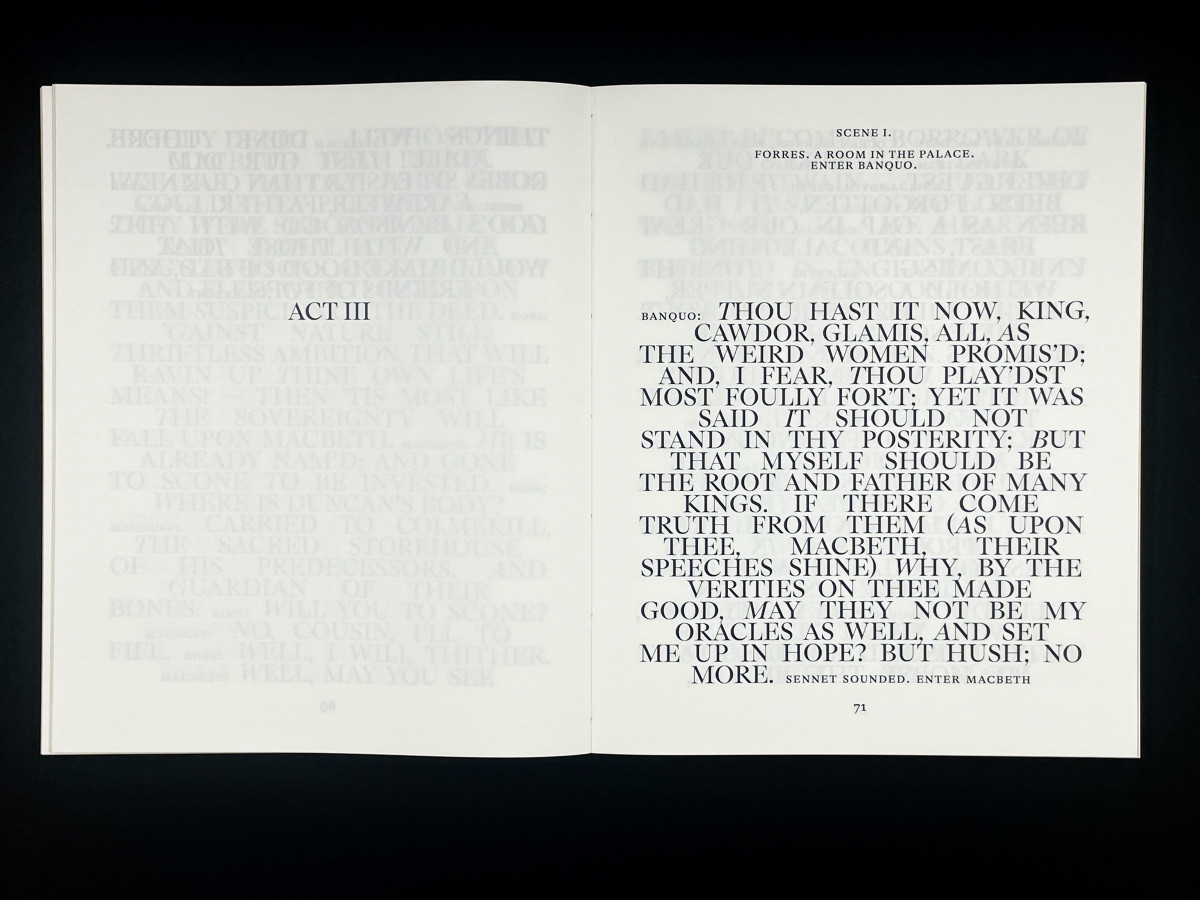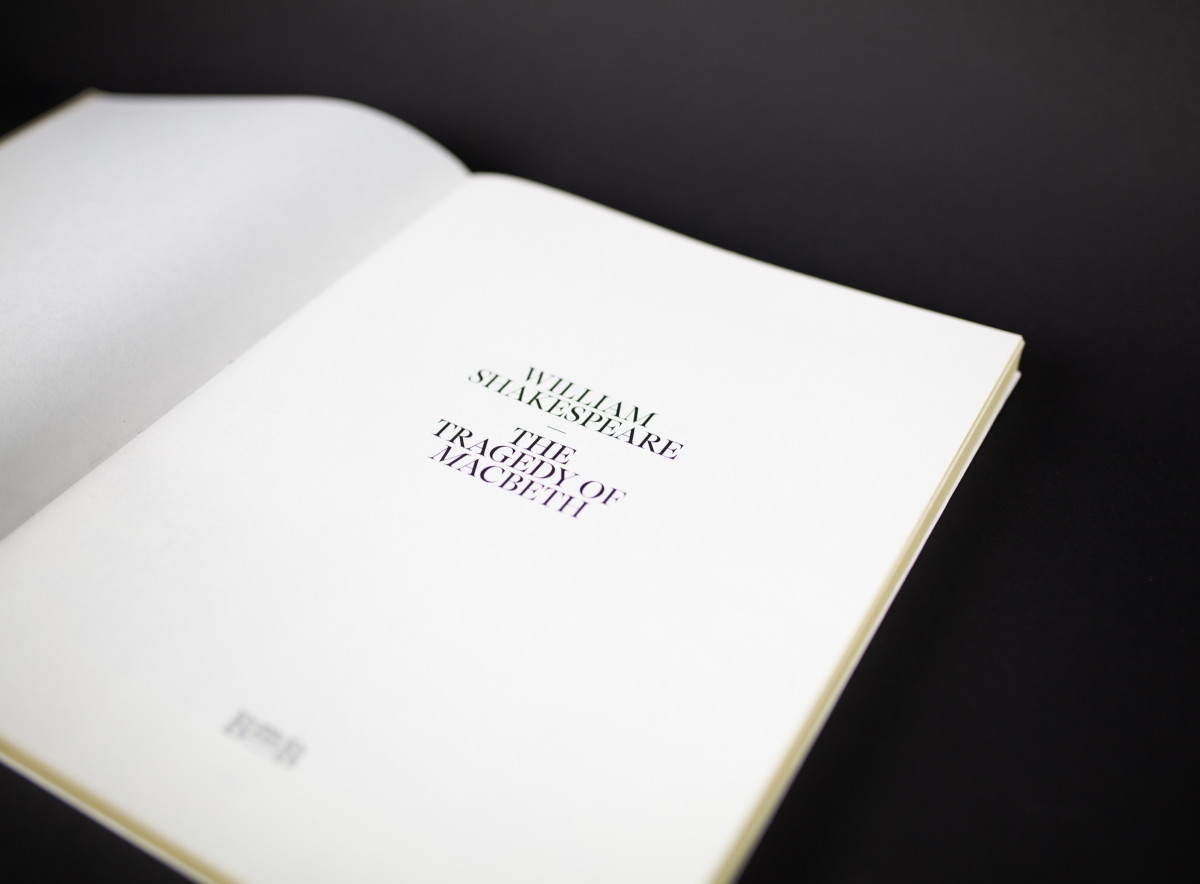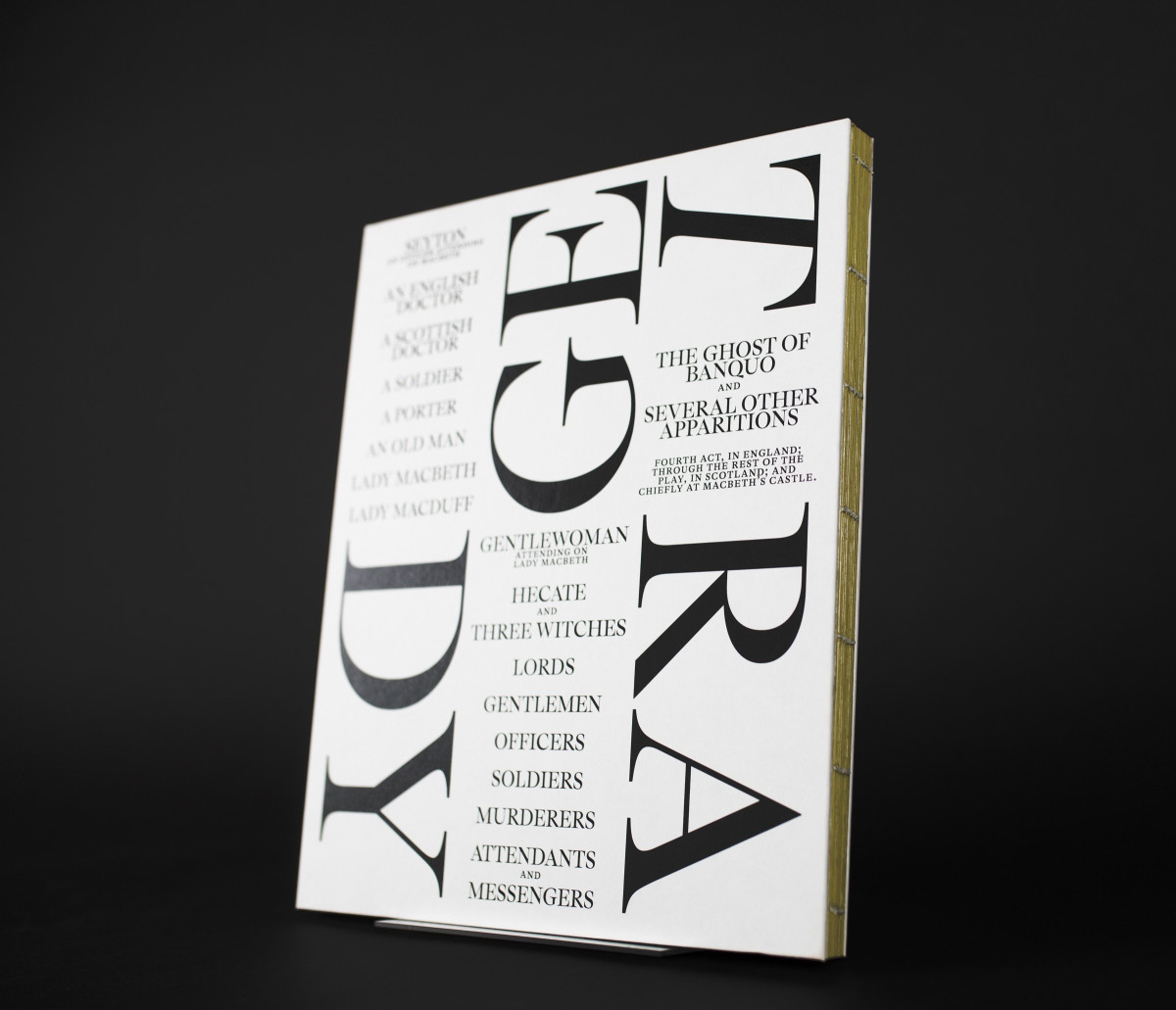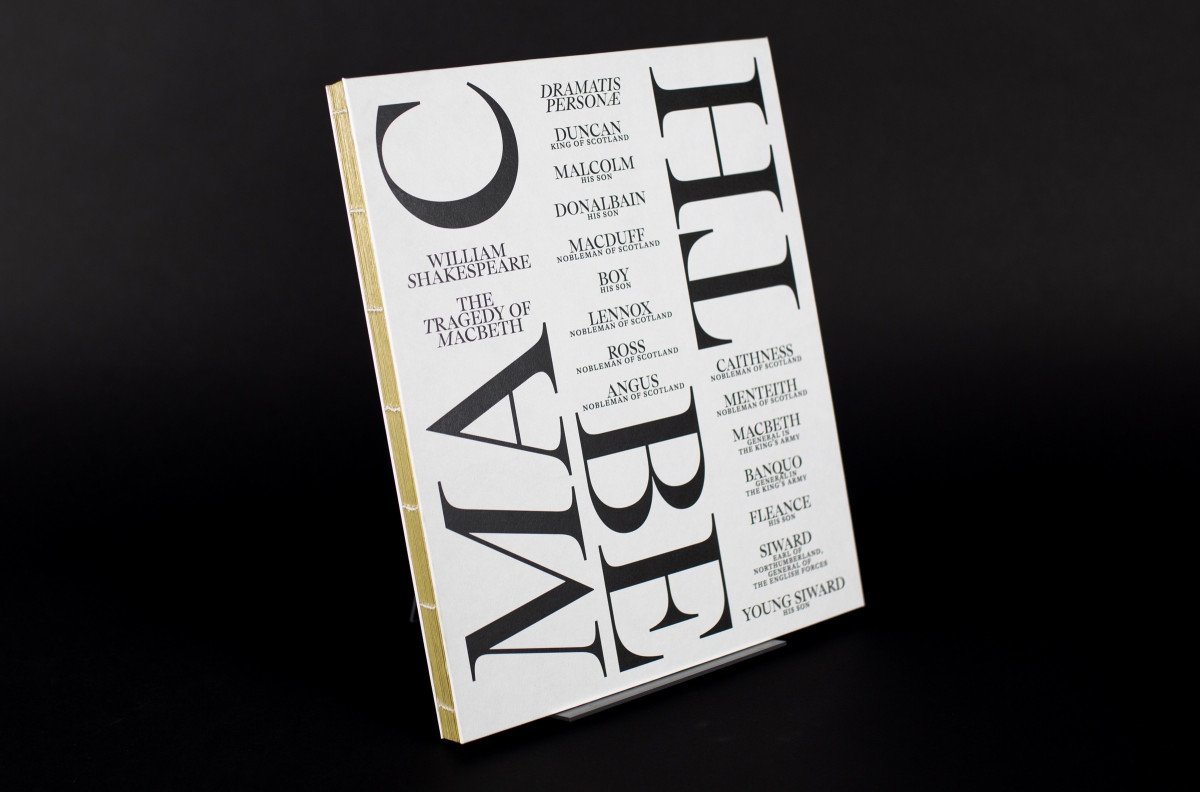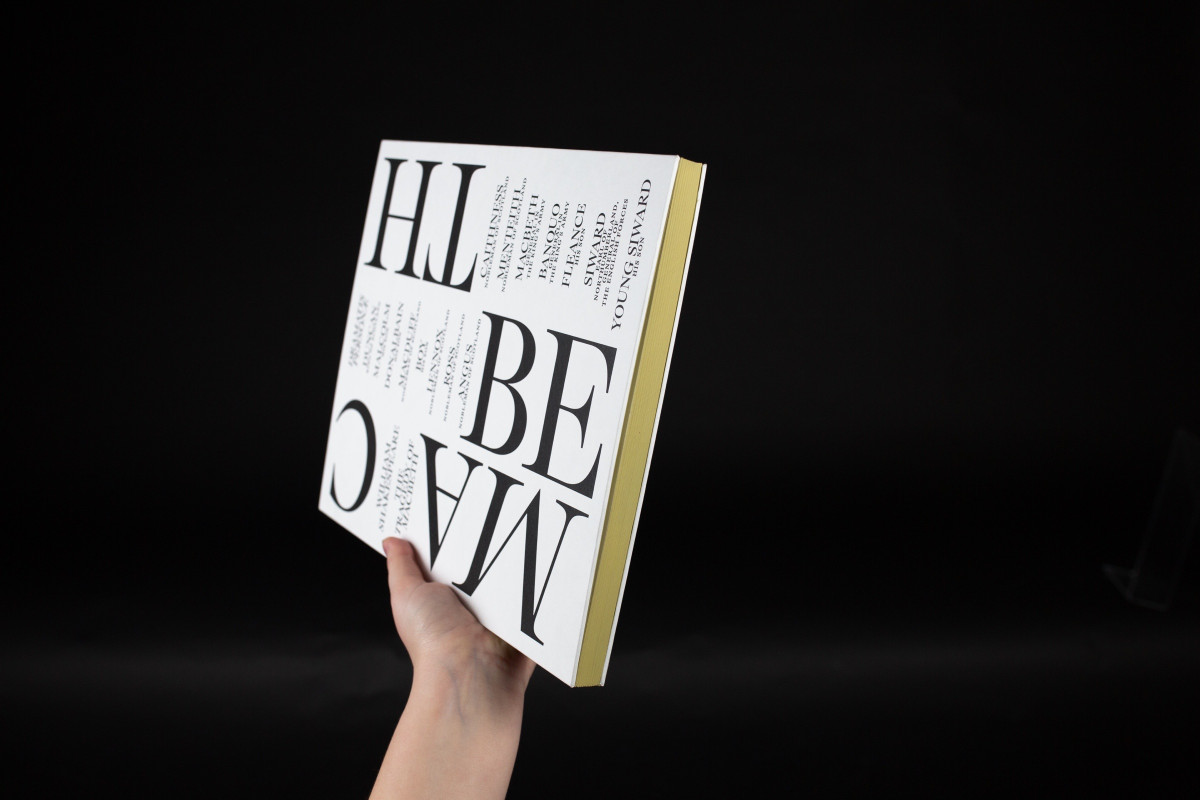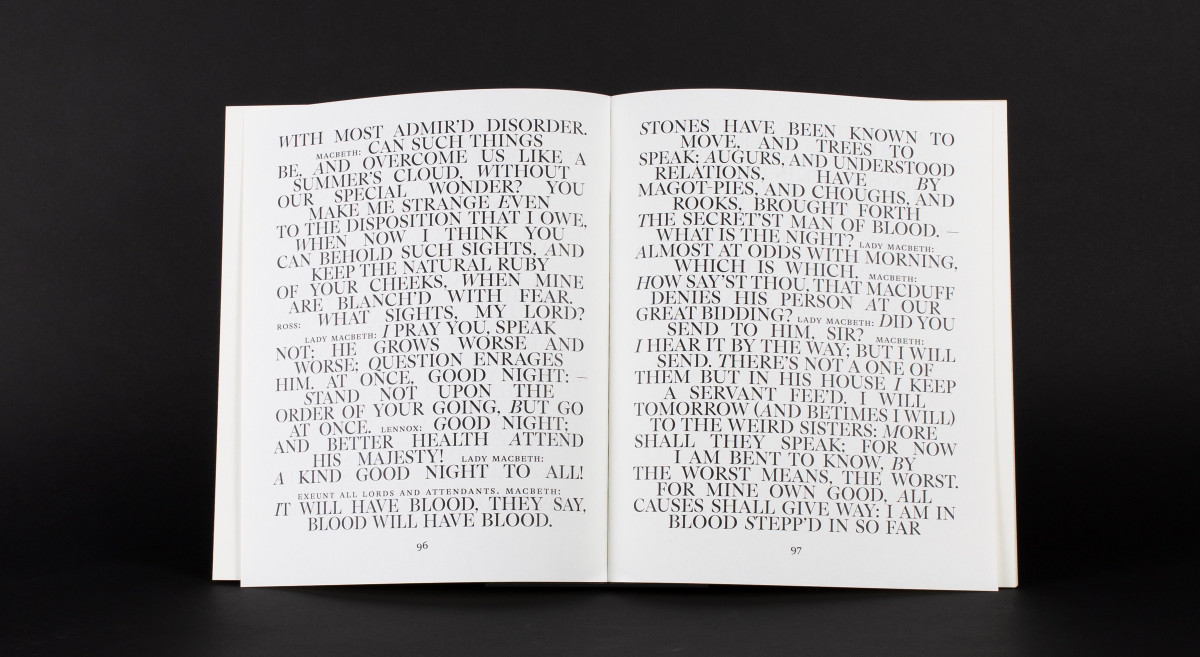
Die experimentelle Buchgestaltung zu Shakespeares Macbeth setzt sich mit dem inneren Verfall der Titelfigur auseinander – einem psychologischen Abstieg, der sich visuell und typografisch manifestiert. Ausgangspunkt ist die Frage, wie sich die Schattenhaftigkeit Macbeths und die sprachliche Komplexität des Dramas in eine gestalterische Form übersetzen lassen. Durch die Reduktion auf Schwarz-Weiß, eine übersteigerte Typografie in Versalien und gezielte Irritationen im Satzbild entsteht ein Textkörper, der den psychischen Zerfall sichtbar und körperlich erfahrbar macht. Die Sprache Shakespeares wird nicht erklärt, sondern auf typografischer Ebene gespiegelt – als Struktur von Macht, Schuld und Auflösung.
This experimental book design explores the psychological decay of Macbeth and how his descent—marked by shadow, guilt, and ambition – can be translated into typographic form. Central is the question of how Shakespeare’s dense, rhythmic language and the character’s inner fragmentation can be rendered visually. Using only black and white, oversized capital letters, and disrupted typesetting, the layout becomes a reflection of Macbeth’s unraveling mind. Shakespeare’s text is not illustrated but mirrored typographically – as a system of power, collapse, and disintegration.